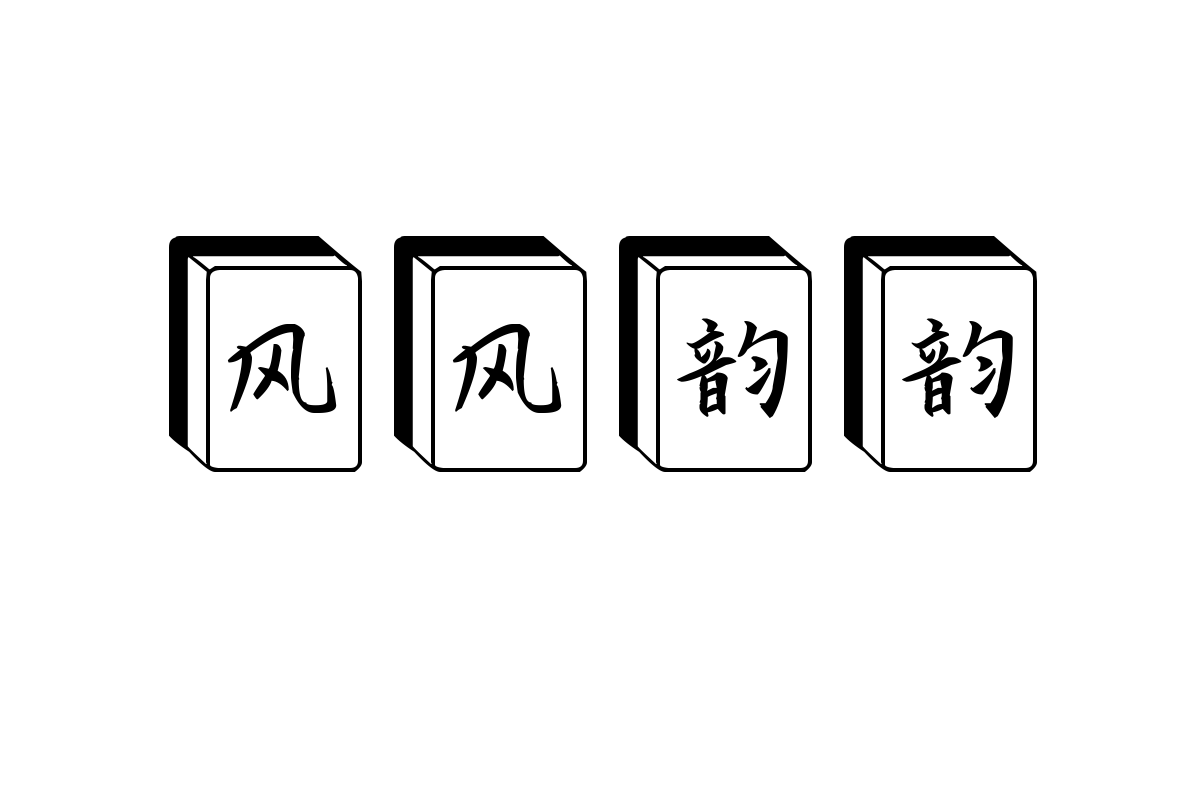
汉呈四方来财体,又称“汉呈体”,是一种书法字体。它的字形结构独特,笔画流畅,线条优美,具有很高的艺术价值和观赏性。这种字体的特点是笔画粗细适中,线条起伏有致,给人以优雅、大方的感觉。同时,它的字形结构也具有一定的对称性和平衡感,使得整体效果更加和谐美观。
汉呈四方来财体的主要特点是其笔画的粗细变化较大,既有细如发丝的细小笔画,又有粗如椽木的粗壮笔画。这种粗细变化使得整个字形显得层次分明,富有变化。此外,这种字体的笔画也具有一定的流动性,使得整个字形看起来更加生动活泼。
总的来说,汉呈四方来财体是一种非常独特的书法字体,它以其优美的字形结构和独特的艺术风格,受到了广泛的欢迎和喜爱。